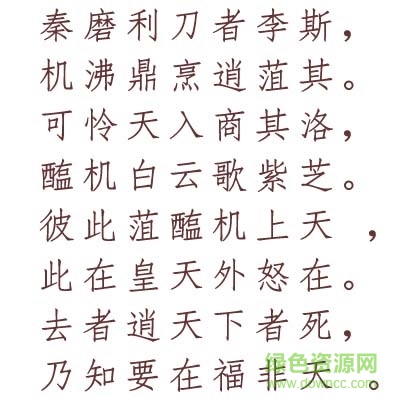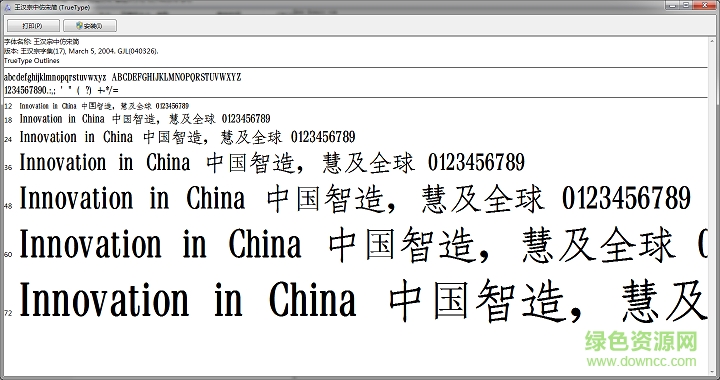
王漢宗中仿宋簡(jiǎn)是一款美觀的簡(jiǎn)體王漢宗字體,沿襲了宋體工整細(xì)膩的特點(diǎn),略加歪斜的感覺,看起來不那么死板,顯得非常有個(gè)性,歡迎喜愛的朋友到綠色資源網(wǎng)下載體驗(yàn)!
筆畫略粗的仿宋字體。該字體在宋體的基礎(chǔ)上進(jìn)行了改進(jìn),筆畫加粗,部分字向右上翹起,很飄逸的感覺。